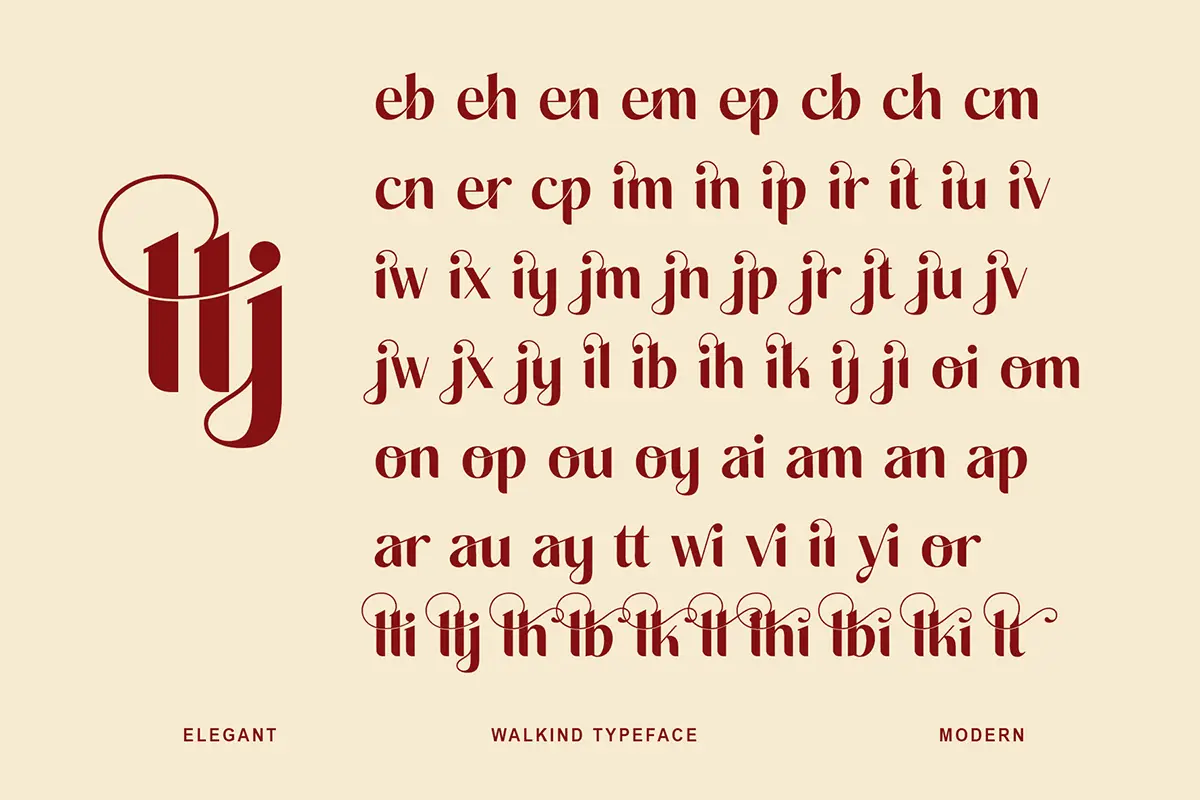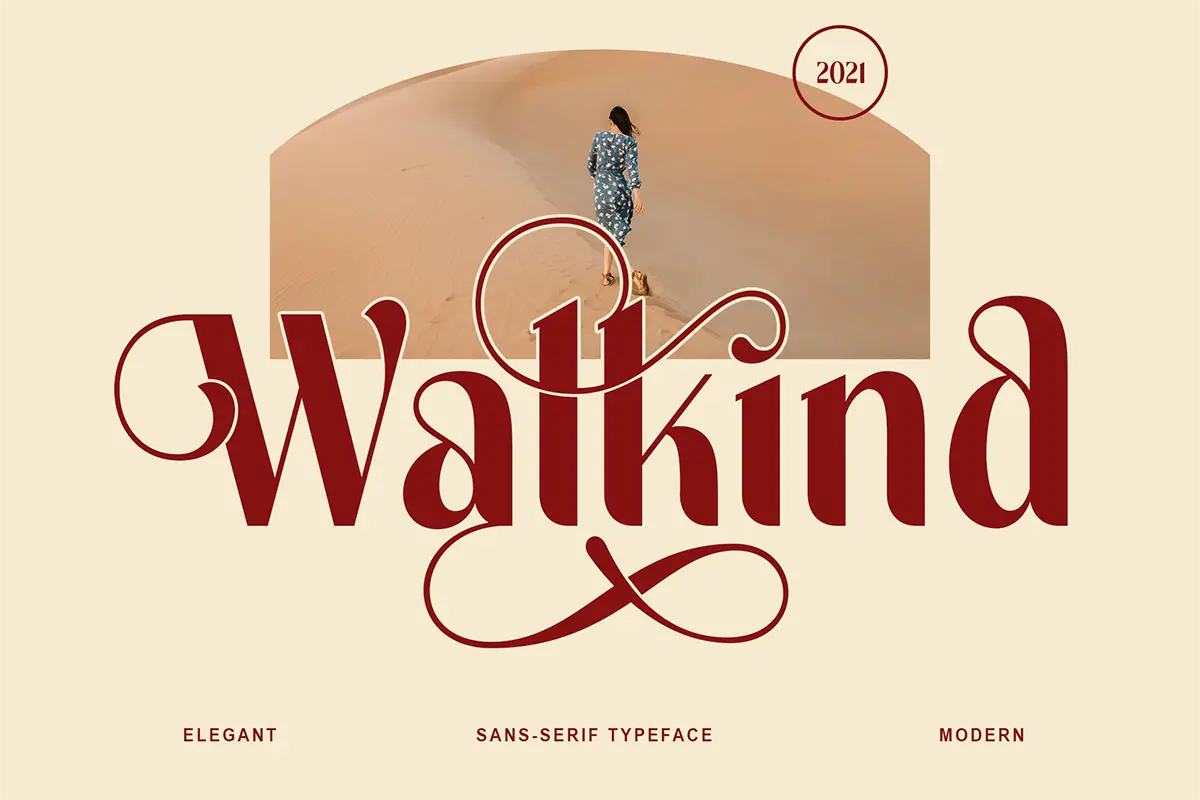
فونت سریف شیک و استایلیش
Walkind یک فونت سریف شیک، استایلیش و بسیار ظریف است که با ترکیب زیبایی از خطوط کلاسیک و جزئیات مدرن طراحی شده. این فونت بهصورت PUA Encoded ارائه میشود؛ یعنی تمام گلیفها و سوئیشها بهراحتی قابل دسترسی هستند و میتوانید بدون دردسر از تمام کاراکترهای تزئینی آن استفاده کنید. اگر به دنبال یک فونت حرفهای برای پروژههای لوکس، ادیتوریال یا برندینگ هستی، Walkind انتخابی مطمئن و چشمگیر است.
⭐ ویژگیهای فونت
- سبک Serif شیک و مدرن
- PUA Encoded برای دسترسی آسان به تمام گلیفها و سوئیشها
- مناسب برای برندینگ، طراحی ادیتوریال و پروژههای لوکس
- ظاهر ظریف، متعادل و حرفهای
- عملکرد عالی در لوگوتایپها و تایپوگرافیهای تزئینی
🎯 موارد استفاده
- طراحی لوگوهای ظریف و لوکس
- مجلات، پوسترها و ادیتوریالها
- بستهبندی محصولات پریمیوم
- کارت دعوت، کارت ویزیت و تایپوگرافیهای هنری
- پروژههای فشن، زیبایی و برندهای مینیمال